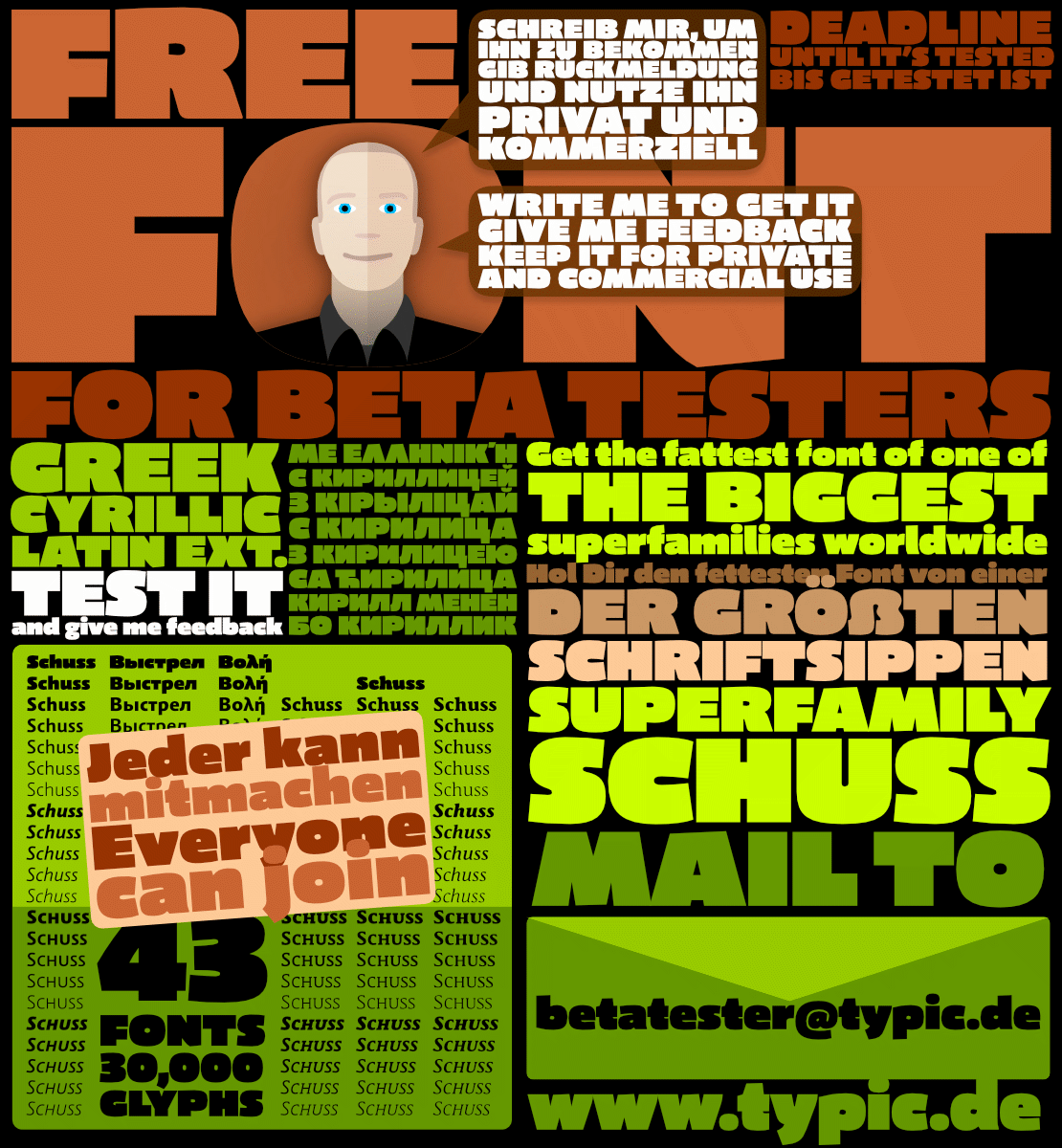
Wer hilft mir, den Font zu testen? Jeder kann mitmachen!
Who helps me testing the font? Everyone can join!
Dann würde ich, ohne dass ich mir den Font geholt habe, doch gleich mal beim hier so geliebten ẞ anfangen. das hier ist mir zu klein-ß-ig
Danke Catfonts, Du bringst es auf den Punkt. Wenn es schön klein-ß-ig ist, wird es von mehr Lesern erkannt. Nur wenige da draußen beschäftigen sich mit dieser Ligatur. Aber als Schriftgestalter möchte ich, dass sie es trotzdem lesen können.
So habe ich das allerdings nicht gemeint.
Ich meinte, wenn man schon einen Großbuchstaben, und das ẞ / ß sind Buchstaben, keine Ligaturen, wie ja auch W und w, die einst mal VV und vv waren) bereit stellt, sollte er auch wie ein Großbuchstabe aussehen, und eben nicht wie ein zwiebelfischiger Kleinbuchstabe im falschen Fach des digitalen Setzkastens.
Es werden ja gerade allerorten Fonts nachgerüstet, und so wird auch der Großbuchstabe bald an Bekanntheit gewinnen. Ein Problem, ein Wort mit ẞ zu lesen, konnte ich bei meinen Umsetzungen noch nicht finden.
Wenn Du mit meinem Namen ins Ausland fährst, werden Dir die Schwierigkeiten anderer Menschen mit dem fremden Buchstaben auffallen. Da die zunehmende Globalisierung nach Vereinfachung, statt nach Verkomplizierung schreit, verstehe ich nicht, warum wir hier auf ein völlig anderes Design von Groß- und Kleinbuchstabe setzen sollten.
Ich möchte, dass meine Schriften schnell erfaßt werden können. Der Zeitgeist vom Einsatz zierend verbundener Ligaturen erfüllt im Logodesign einen vertretbaren Zweck, zwingt den Leser von Fließtext aber zum Stocken. Buchstaben oder Ligaturen, die zu weit vom gewohnten Bild abrücken erschweren die schnelle Erfaßbarkeit und somit den Lesefluß.
Auch wenn viele Fonts bald angepasst sein werden, wird das kapitale ß kaum zu sehen sein. Nur wenige Anwender werden es zu benutzen wissen. Und selbst jemand wie ich, der es in seinen Schriften gerne zeigen möchte und es sogar im Namen trägt, vermeidet es, sich fortwährend in Großbuchstaben zu schreiben.
In erster Linie soll sich die neue Majuskel doch ins Satzbild einfügen, also nicht wie meist üblich, über die Versalhöhe hinausragen. Weite und Grauwert sind ebenfalls anzupassen.
Mir schien die Enstehungsgeschichte des gemeinen scharfen 's' aus zwei 's' (lang und rund) naheliegender, als die mit dem langen 's' und dem 'z'. So leite ich die neue versale "Ligatur" auch aus zwei großen 'S' ab.
Resümierend behaupte ich hier also ganz frech, ein großes scharfes 'S', das dem Gemeinen ähnelt, wird sich langfristig durchsetzen. Um was wetten wir?
Bildbeispiele zur Bundesligatur
vor 24 Minuten schrieb jochen schuß:
Resümierend behaupte ich hier also ganz frech, ein großes scharfes 'S', das dem Gemeinen ähnelt, wird sich langfristig durchsetzen. Um was wetten wir?
Hier werden zwei Dinge vermischt. S und s ähneln sich auch, weil sie das gleiche Konstruktionsprinzip besitzen. Sie haben aber nicht die gleichen Proportionen. Ein s fügt sich nicht in den Versalsatz. Und ein ß eben oft auch nicht. Der Lesbarkeit wegen darf das das große Eszett also gern dem kleinen ähnlich sehen, es muss sich aber gleichzeitig im Sinne der Proportionen und Metrik in reinen Großbuchstabensatz fügen. Dies wurde im obigen Fall als nicht erfüllt kritisiert und ich schließe mich dem an.
Was dem ẞ so einen zwiebeligen Fischgeruch verpasst, ist dieser kleine Schwung unten am linkemn Stamm, den man sonst ja in keiner Majuskel findert. Würde der Buchstabe hier mit einem geraden Bein fest auf dem Boden stehen, wäre die sonst noch große Ähnlichkeit zum ß bestimmt vertretbar.
Und was die Wette anbelangt, würde ich, hätte ich grad einen vernünftigen Wetteinsatz zur Verfügung, alles darauf wetten, dass sich letztlich Formen des ẞ durchsetzen, die zwar vom Grundskelett her dem ß ähneln (wie hier ja wohl auch ẞ und ß), aber eben doch deutlich als Majuskel erkennbar sind, und sich eben auch in den Formenkanon der Majuskeln der jeweiligen Schrift einpassen.